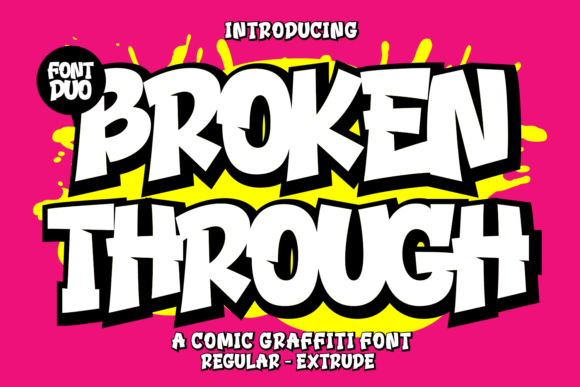
Broken Through
Trouver les bons éléments de conception peut être un défi, mais Broken Through propose une collection exceptionnelle qui rehausse instantanément votre travail.
Conçu avec précision, Broken Through offre des vecteurs nets, une typographie fluide et une licence commerciale pour une tranquillité d'esprit.